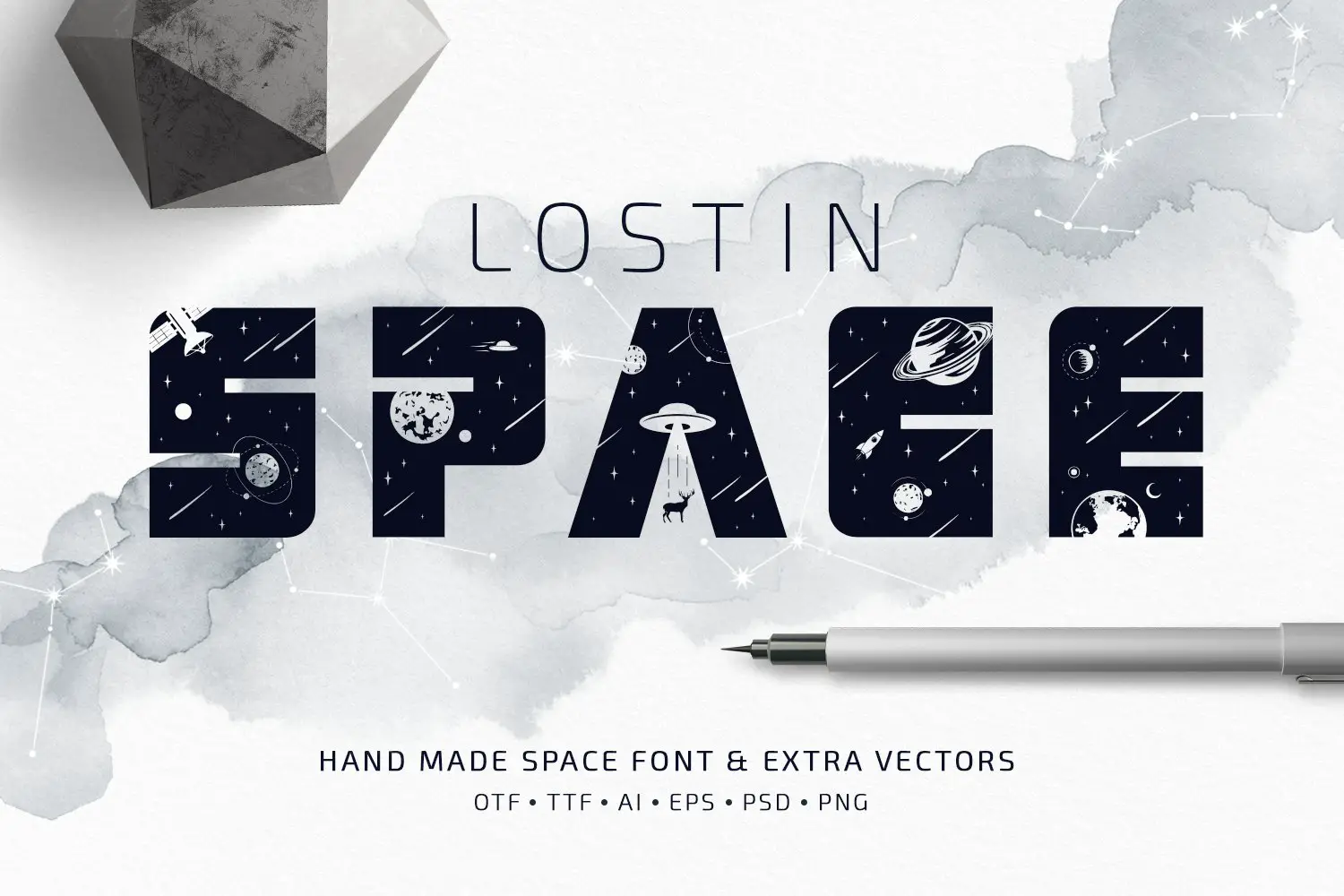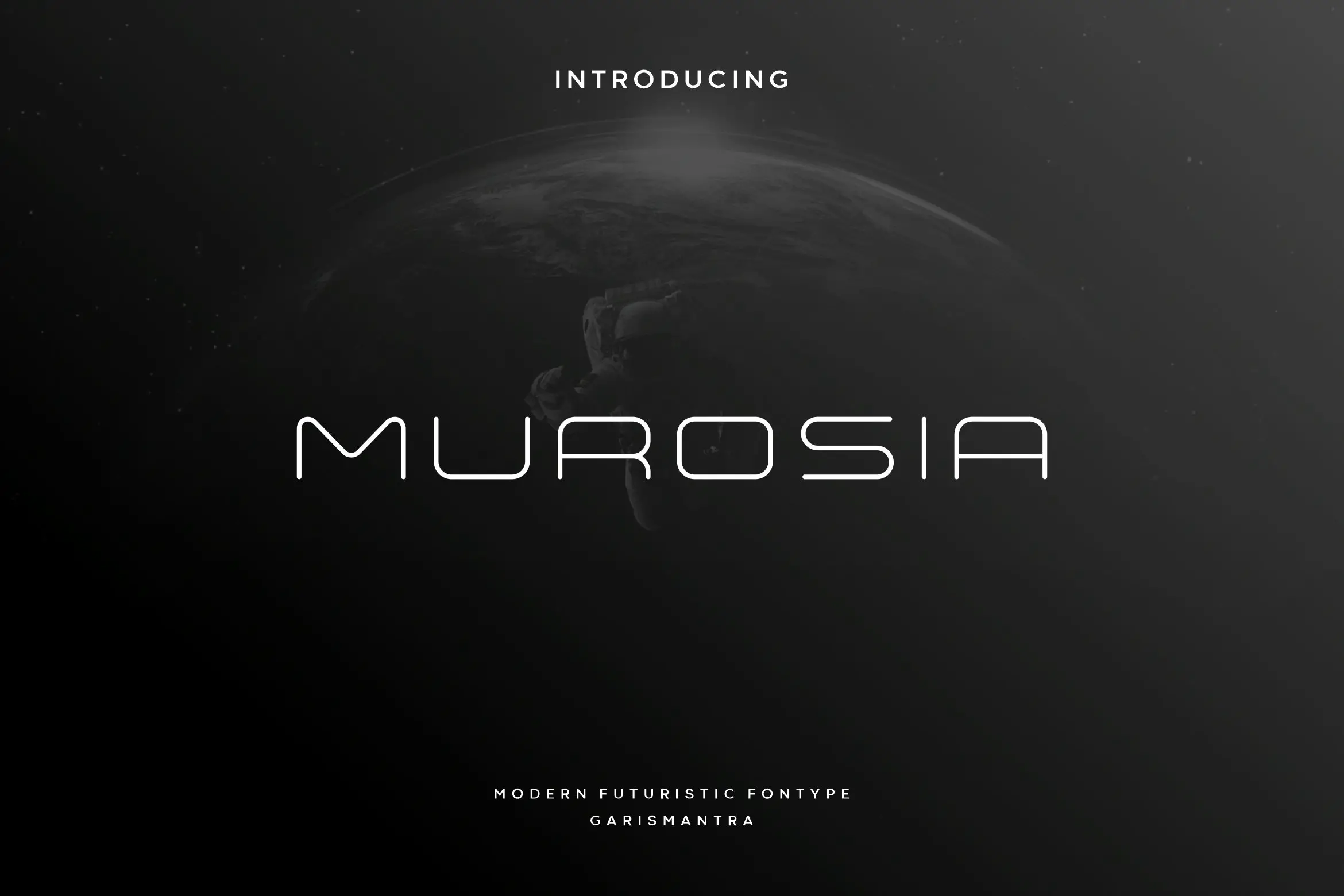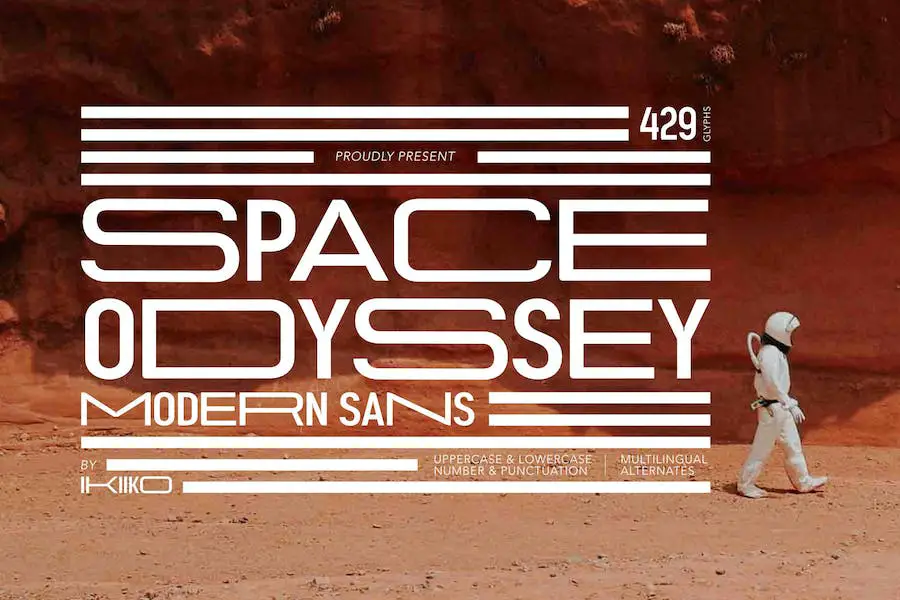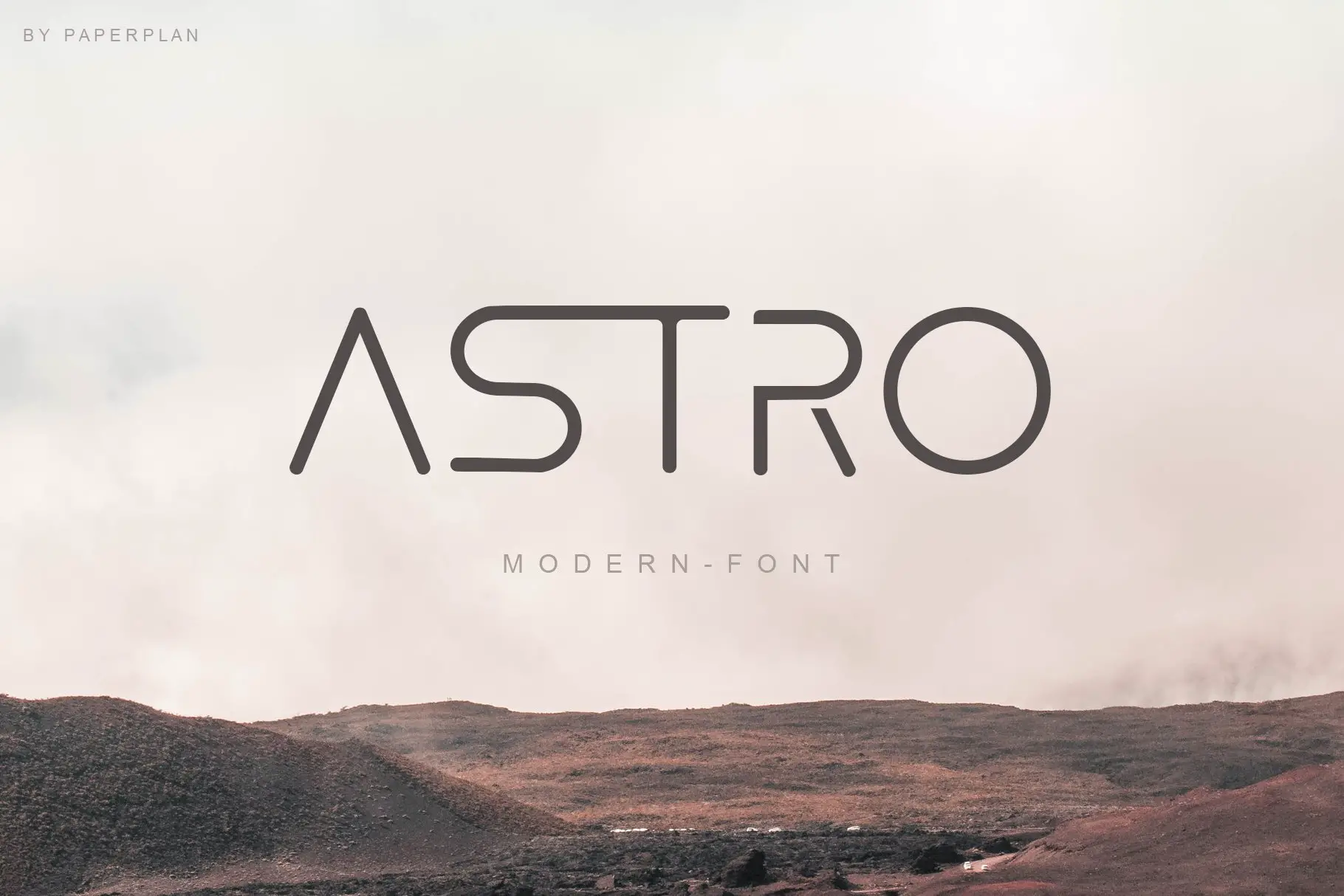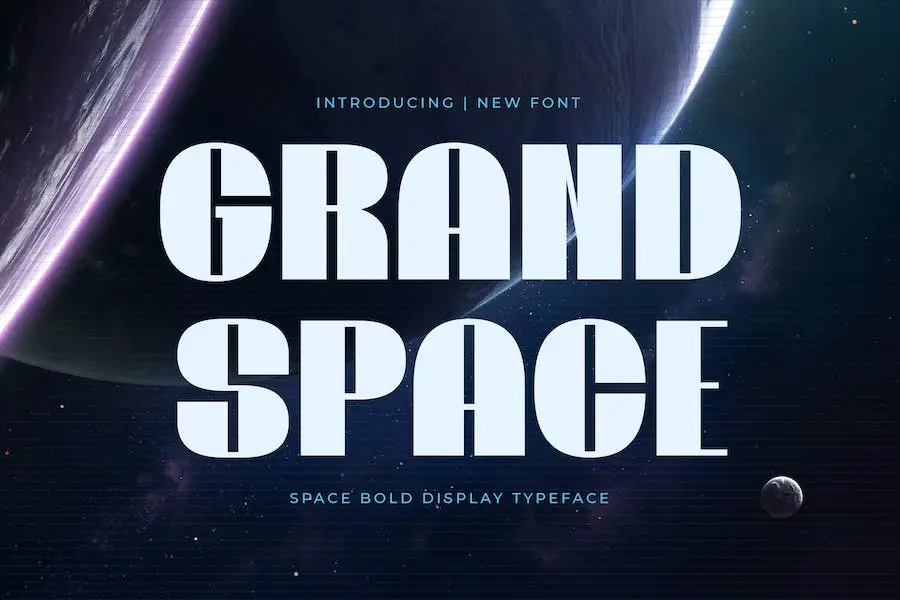
36 najlepszych czcionek kosmicznych 2023 (bezpłatne i premium)
Opublikowany: 2023-04-10Idealna czcionka może sprawić, że Twój projekt będzie się wyróżniał, niezależnie od tego, czy projektujesz logo, tworzysz stronę internetową, czy przygotowujesz prezentację.
Znalezienie idealnej czcionki kosmicznej może być trudne przy tak wielu opcjach. Zebraliśmy więc 36 najlepszych obecnie dostępnych czcionek kosmicznych. Czcionki te wyglądają stylowo, nowocześnie i odważnie, więc nadadzą Twojemu projektowi dodatkowy impuls.
Niesamowite możliwości oferowane przez czcionki kosmiczne są nieograniczone. Od projektów inspirowanych stylem retro po futurystyczne style — każdy znajdzie tu coś dla siebie. Więc jeśli szukasz galaktycznego stylu dla swojego projektu, oto czcionki, na które powinieneś patrzeć!
Najlepsze czcionki kosmiczne premium
Na szczęście do wyboru jest wiele czcionek premium, z których każda ma swój własny, niepowtarzalny styl. Możliwości są nieograniczone, od futurystycznych krojów cyberpunkowych po oldskulowe skrypty pędzla.
W tym artykule dowiesz się wszystkiego o najlepszych czcionkach kosmicznych premium, których możesz użyć!
Centauri
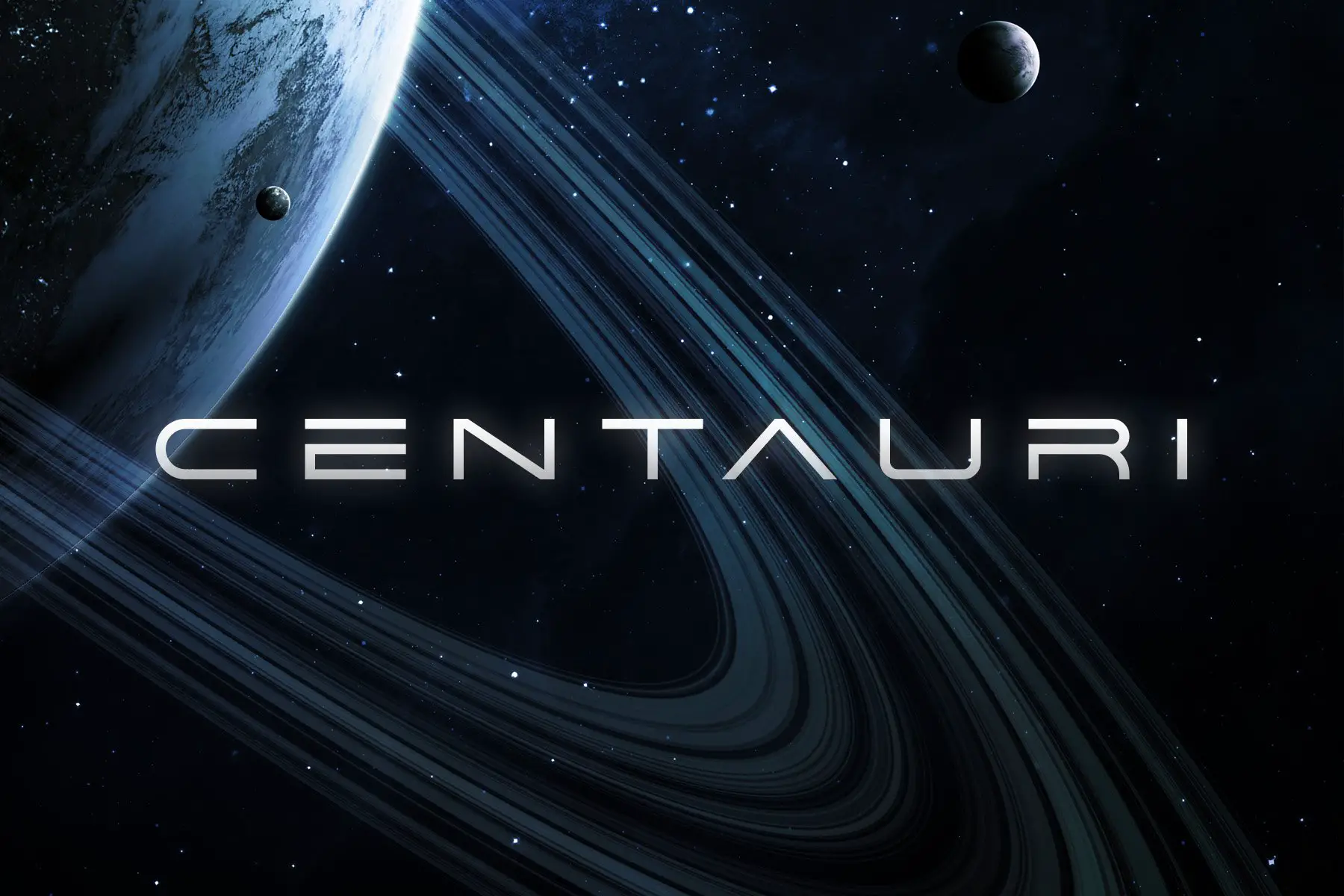
Centauri to doskonały wybór dla każdego projektanta, który chce się wyróżnić. Odważny wygląd i wszechstronne funkcje sprawiają, że idealnie nadaje się do tworzenia przyciągających wzrok projektów, które wyróżniają się z tłumu. Jeśli szukasz futurystycznej czcionki o ogromnym potencjale twórczym, Centauri jest idealnym wyborem.
Szerokimi literami znacznie wyróżnia się na tle tradycyjnych czcionek. Dodatkowo alternatywne litery nadają twoim projektom trochę więcej różnorodności i kreatywności. Za pomocą tej czcionki możesz tworzyć unikalne słowa i wiadomości ze względu na jej symbole interpunkcyjne. Liczby dają jeszcze więcej możliwości
Przestrzeń MBF
MBF Space to nowoczesna, cienka, zaokrąglona czcionka zaprojektowana przez Moon Bandit, która dodaje każdemu projektowi futurystyczny klimat science-fiction. Jego wysoka przejrzystość sprawia, że idealnie nadaje się do tworzenia plakatów, tytułów, logo, nagłówków i nie tylko.
Dzięki gładkim krzywiznom i czystemu projektowi czcionka wygląda świetnie w każdym rozmiarze. MBF Space nadaje Twoim projektom futurystyczny wygląd, a jednocześnie jest czytelny. Niezależnie od tego, czy jesteś grafikiem, czy po prostu chcesz dodać kreatywnego akcentu do swojej pracy, ta czcionka jest doskonałym wyborem.
Kolorowa przestrzeń
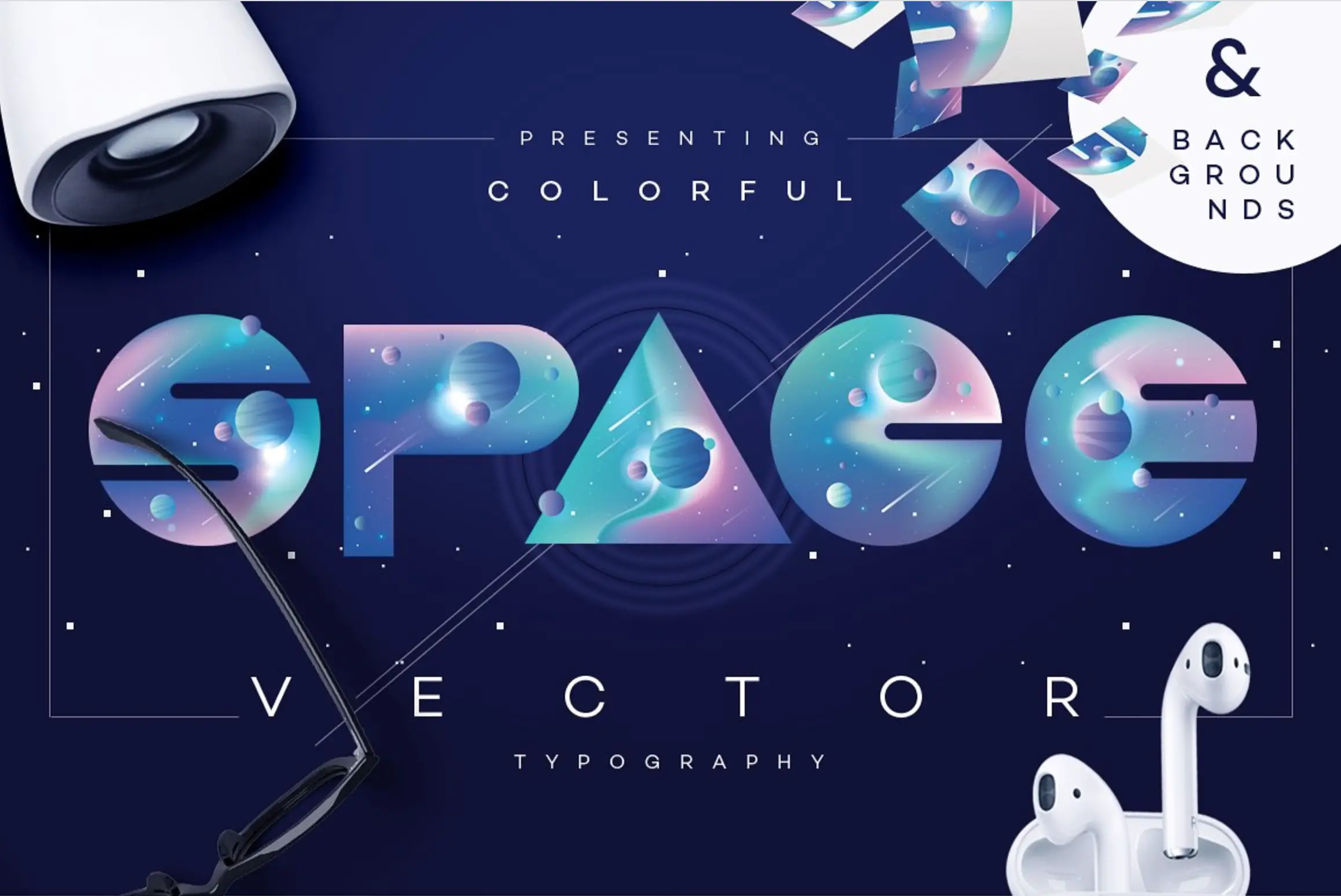
W „Kolorowej przestrzeni” będziesz mógł odkrywać cuda kosmosu na wyciągnięcie ręki. Możesz używać tej czcionki w projektach internetowych lub drukowanych, ponieważ zawiera ona piękne ilustracje planet, gwiazd i komet. Dla grafików, którzy chcą wyróżnić się z tłumu i dodać odrobinę fantazji do swoich projektów, jest to idealne rozwiązanie.
Dzięki tej czcionce możesz z łatwością tworzyć urzekające logo, przyciągające wzrok plakaty lub ekscytujące zaproszenia. Żywe kolory i misterne szczegóły każdej litery ułatwiają wyrażanie siebie w naprawdę wyjątkowy sposób. Sprawdź „Kolorową przestrzeń” już dziś i daj się ponieść kreatywności!
Czas, przestrzeń
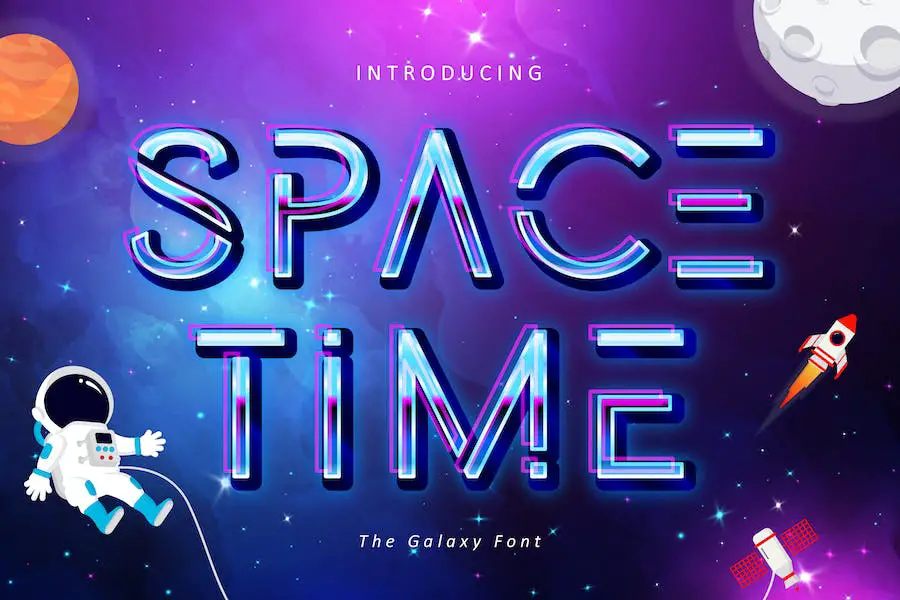
Dzięki doskonałej czytelności i przejrzystości Space-Time jest jedną z czcionek kosmicznych, których można używać zarówno w małych, jak i dużych projektach. Jego wszechstronność sprawia, że doskonale nadaje się do użytku z innymi czcionkami i świetnie wygląda w połączeniu z nimi.
Niezależnie od tego, do czego używasz tej czcionki, wiesz, że nada ona Twojemu projektowi wyjątkowy charakter i uczyni go bardziej atrakcyjnym. Jest wspaniały do tworzenia nagłówków, logo, projektów stron internetowych i odzieży, aby nadać Twojej pracy nowoczesny charakter. Oprócz zapewniania pięknych krzywych i linii, jest łatwy do odczytania i łatwy w obsłudze.
Spojrzenie w gwiazdy
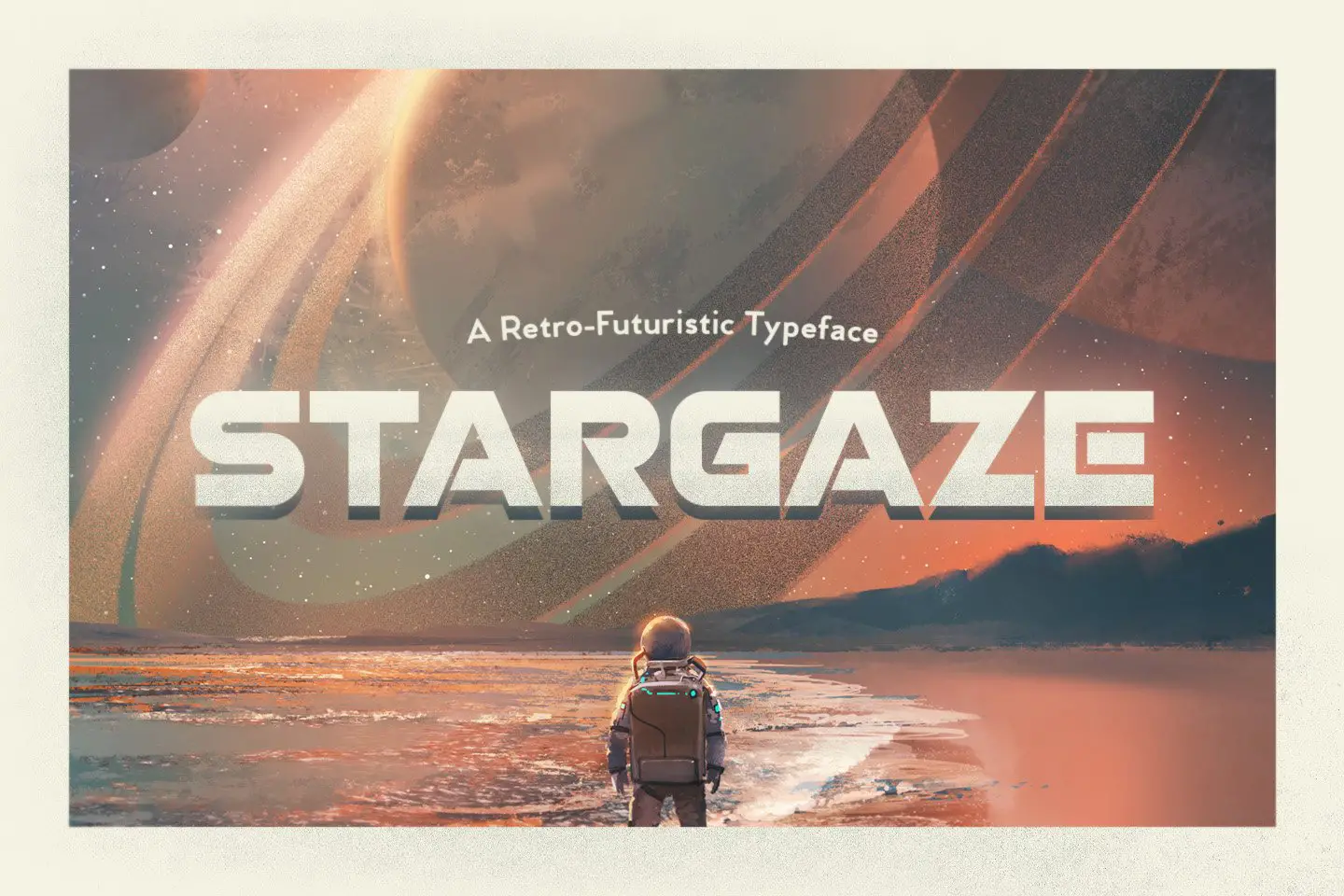
Stargaze ma w sobie coś wyjątkowego. Ma retro, futurystyczny klimat science-fiction, który jednocześnie przyciąga wzrok i jest wszechstronny. W przypadku wersji zwykłej i szablonowej możesz łączyć zaokrąglone i ostre rogi, aby Twoja czcionka wyróżniała się.
Czcionka Stargaze zawiera wielkie wielojęzyczne litery, cyfry, znaki interpunkcyjne i — jako dodatkowy bonus — niektóre litery z szablonu mają odwrócone wersje, które można aktywować za pomocą klawisza Caps Lock. To sprawia, że czcionka jest niezwykle przydatna do różnych celów, od logo po tytuły filmów.
Przestrzeń
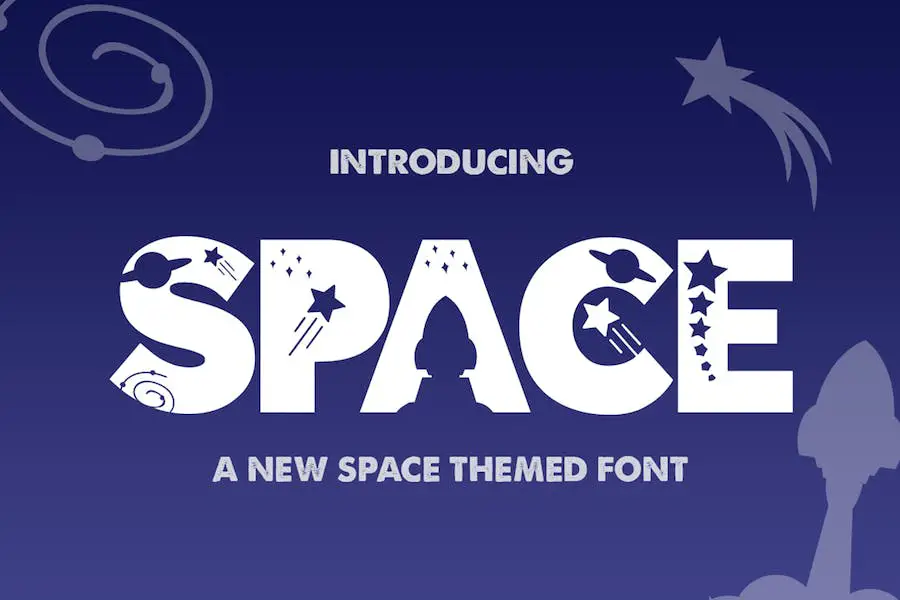
The Space to wyjątkowa czcionka, która dodaje odrobinę tajemniczości i cudowności każdemu projektowi. Jest idealny do wszystkiego, od logo po plakaty, i jest dostępny w dwóch wersjach: Space Silhouette Font w formatach OTF i TTF, a także czcionki internetowe w formatach EOT, SVG, WOFF i WOFF2.
Jest to odważna, a jednocześnie elegancka czcionka z zaokrąglonymi krawędziami i subtelnymi krzywiznami, które sprawiają, że każdy znak na stronie wydaje się żywy. Zaokrąglone krawędzie i subtelne krzywizny sprawiają, że wyglądają jak żywe. Optycznie dopasowane kształty sprawiają również, że Twoje projekty są łatwe do odczytania i czytelne, dzięki czemu będą się wyróżniać bez utraty przejrzystości.
Wniosek